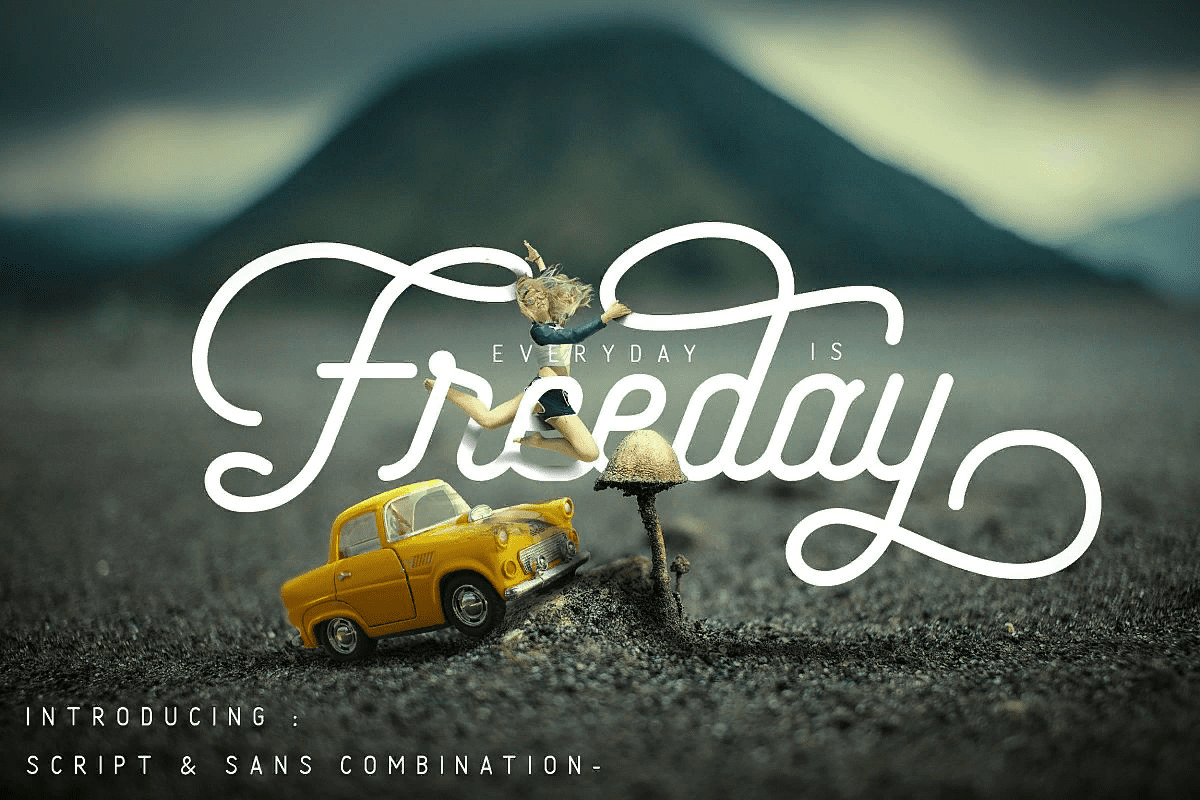
Название: Freeday Font (2021)
Freeday Font - это современный шрифт с большим количеством функций, сделанный с любовью
. Freeday Font имеет полный набор глифов, этот шрифт подходит для свадебных приглашений, поздравительных открыток, футболок, логотипов или любого дизайна, который вы создаете. В комплект входит полный набор стандартных символов, альтернативы, вариации вязи, пунктуация и дополнительная текстурированная версия для вашего дизайна и многое другое.